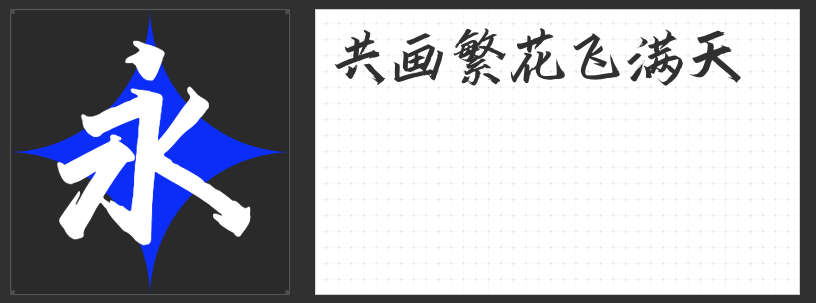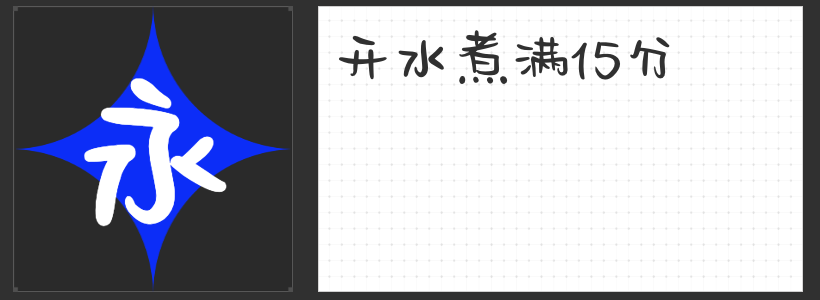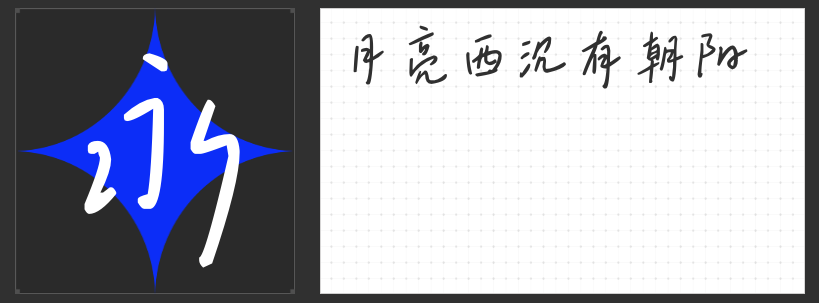
Vlog标题字体推荐:四款风格化字体解锁视觉吸引力
在短视频内容竞争激烈的当下,Vlog的标题设计已成为吸引观众注意力的关键。一款独特的字体不仅能强化视频主题,更能通过视觉语言传递情绪与风格。以下四款字体各具美学特质,从随性手写到童趣稚拙,从酣畅书法到俏皮可爱,为Vlog标题提供多元化的创意选择。
1. 字圈也字绮梦手迹
这款字体以“整体大于部分”的设计哲学脱颖而出。单字看似笔画各异、无规律可循,但当它们组合成句时,却能自然形成一种慵懒随性的视觉节奏。复杂与简单的字形相互交织,既无疏离感,又充满取长补短的和谐美感。其风格融合了传统书写的底蕴与现代审美的个性,仿佛一笔一画间都在诉说年轻创作者的故事。适合旅行、生活记录类Vlog,传递自由不羁的态度。
2. 小豆岛默陌乐童简
以孩童书写为灵感,这款字体采用上松下紧的独特结构,笔画宽细一致,稚拙中透着天真。它摒弃了成人书写的规整感,用简单的线条还原童年的无拘无束。无论是亲子内容、宠物日常还是轻松向的分享类Vlog,这款字体都能通过其纯粹的童趣感拉近与观众的距离,营造温暖治愈的氛围。
3. 造字侠今朝醉简
作为毛笔楷书的现代演绎,这款字体以“醉意”为魂——收笔凌厉如剑,笔法正统却暗藏酣畅,劲健雄浑的气势中透着洒脱不羁。它适合文化、历史类Vlog的标题设计,尤其是需要传递力量感或传统韵味的内容。一笔一划间,既能彰显创作者的文化底蕴,又能通过视觉冲击力抓住观众眼球。
4. 字圈也字珍珠奶茶
这款字体的设计灵感源自日常生活中的小确幸,单字尺寸不一的排列方式营造出跳跃的节奏感,仿佛奶茶中的珍珠在杯中轻轻碰撞。其随性可爱的风格与美食、美妆、时尚类Vlog高度契合,能为标题注入轻松活泼的元气,让观众在第一时间感受到内容的趣味性。
四款字体,四种情绪表达。无论是追求艺术共鸣、童真治愈、文化张力还是俏皮灵动,总有一款能成为你Vlog标题的点睛之笔。